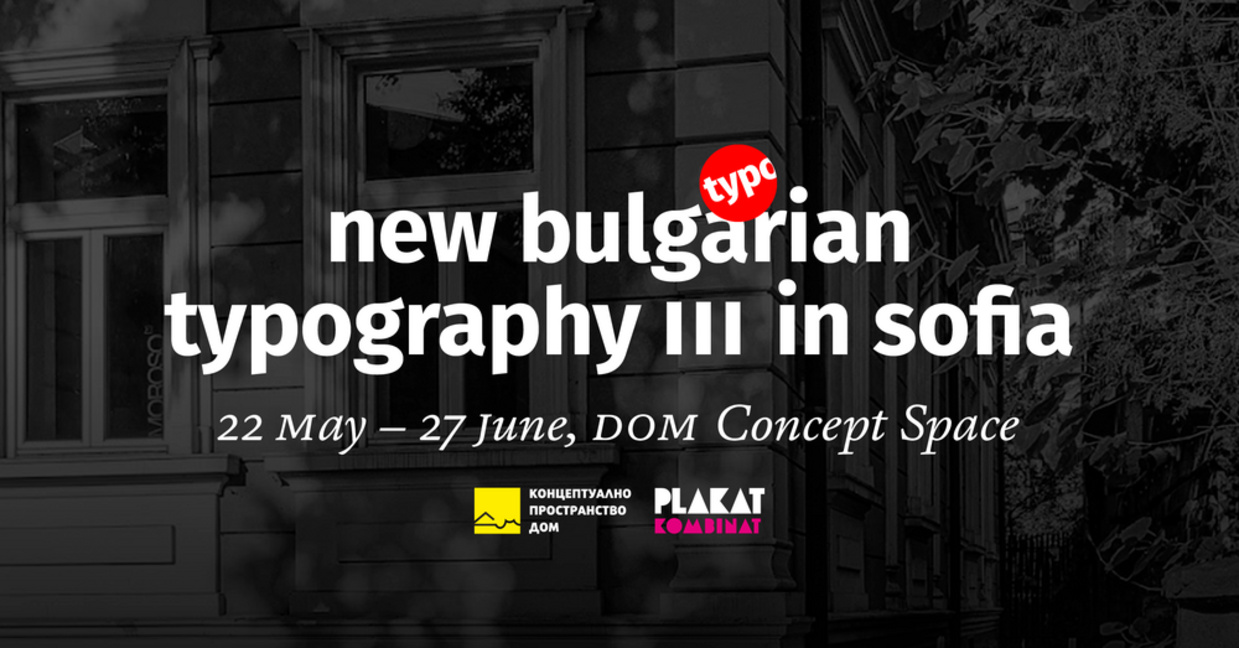
Третото издание на "Нова българска типография" ще бъде представено в ДОМ
Третото издание на "Нова българска типография" – изложбата в Концептуалното пространство ДОМ представя в "Артефир" дизайнерът Борил Караиванов.
Куратор на експозицията, която ще бъде открита днес (22 май), е Кирил Златков. Посетителите на ДОМ ще могат да се запознаят до 27 юни с постиженията на българските дизайнери в областта на калиграфията, шрифтовия дизайн и типографията.
По думите на Караиванов тенденцията в типографията е да се използва все повече българската форма на кирилица, която е феномен от 60-те и 70-те години на ХХ век, когато български дизайнери успяват да предложат реконструкция с цел по-хармоничен облик на азбуката.
Световна тенденция е завръщането на интереса към калиграфията, като все повече стрийтартисти намират място в изложбените зали, казва още Караиванов.
В навечерието на 24 май гостът заявява: "Буквите носят история със себе си, която ние много често не познаваме. Те притежават невероятно интересна еволюция. Ако тя бъде проследена, всичко си идва на мястото. Ако можем да кажем, че нещо сме дали на света – това е една писменост."